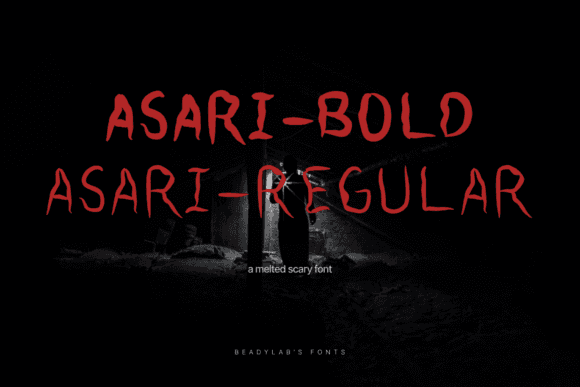
Liberte sua criatividade com a fonte Asari , um estilo assustador desenhado à mão, perfeito para qualquer trabalho artístico ou projeto promocional. Ideal para identidade visual, produtos, pôsteres, flyers e muito mais, ela adiciona um toque único aos seus designs.
- Estilo assustador desenhado à mão
A fonte Asari dá vida aos seus projetos criativos com seu estilo único.